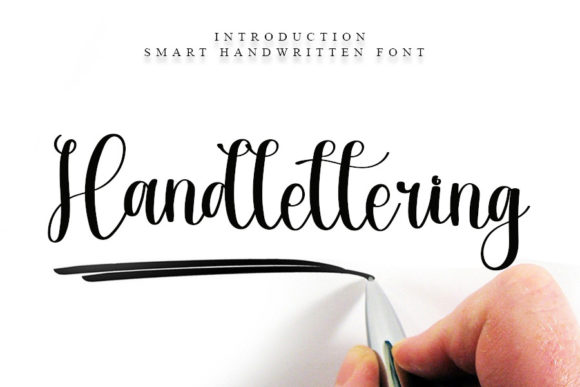
Handlettering
Jika Anda mencari aset berkualitas tinggi seperti Handlettering, paket premium ini adalah pilihan fantastis untuk proyek kreatif Anda.
Dibuat dengan presisi, Handlettering menyediakan vektor yang bersih, tipografi yang halus, serta lisensi komersial untuk ketenangan pikiran Anda.
Baik Anda membuat produk POD (Print on Demand), undangan pernikahan, atau grafis media sosial, Handlettering adalah pilihan yang sangat ideal.